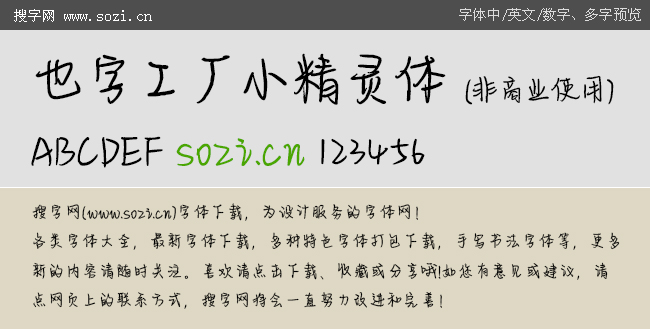
也字工廠小精靈體
搜字網(wǎng)給大家提供一款也字工廠小精靈體(非商業(yè)使用)中文字體下載,也字工廠小精靈體是一款硬筆手寫(xiě)書(shū)法字體,字體筆觸粗細(xì)適中,書(shū)寫(xiě)自然流暢,字形瀟灑大方。適合應(yīng)用于書(shū)籍、海報(bào)、網(wǎng)頁(yè)設(shè)計(jì)等應(yīng)用(此字體為個(gè)人非商用版,商用可以聯(lián)系:官方網(wǎng)址:https://yefont.com/home,聯(lián)系方式:13798980448)。